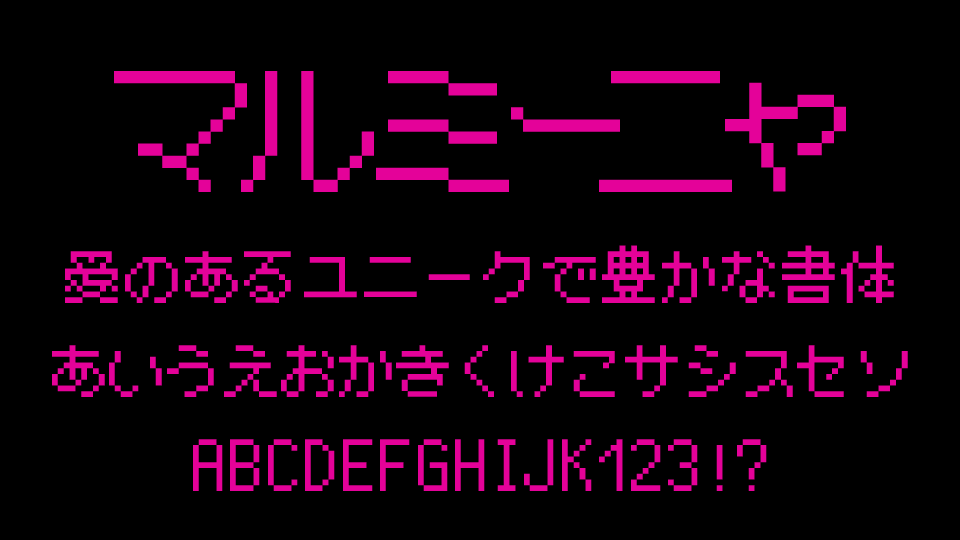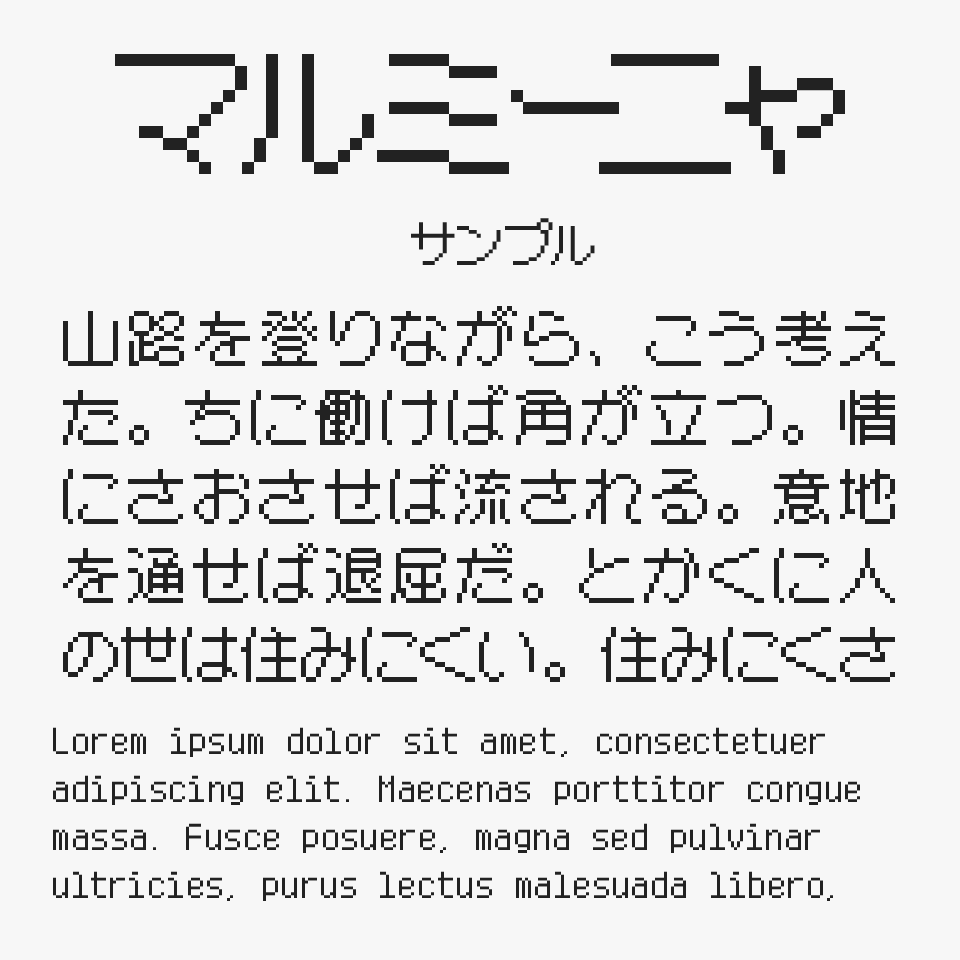
マルミーニャ
マルミーニャフォントは、12ピクセルサイズをベースに制作された、丸ゴシック体のピクセルフォントです。
ドットフォントの中でも“丸ゴシック”タイプは珍しく、カクカクとしたピクセル感を残しながらも、やわらかく親しみやすい雰囲気があります。レトロゲームのような懐かしさがありつつ、どこか素直でまじめな空気感も感じられるところが魅力のフォントです。
一般的なピクセルフォントは無機質で硬めな印象になることも多いですが、マルミーニャは文字にほんのり丸みがあることで、可愛らしさと読みやすさが心地よく混ざり合っています。
丁寧に整理されたピクセルの配置により、ピクセルフォントとしての十分な可読性が優れているフォントです。丸みがあるピクセルフォントは可愛い!
マルミーニャフォントを、ほかのドットフォントと比較してみると、丸ゴシックならではのやわらかい空気感が特に際立っているドットフォントです。
比較しているフォントは、「ベストテン」「魔導太丸ゴシック」「マルモニカ」「あいこの未来クラブ」もそれぞれのコンセプトがあるドットフォントなので、あわせて比較しながらチェックしてみてください。
収録文字は、ひらがな ・カタカナ ・英数字 ・JIS第1水準漢字2965字、第2水準漢字3390字・各種記号が収録されているとのことです。